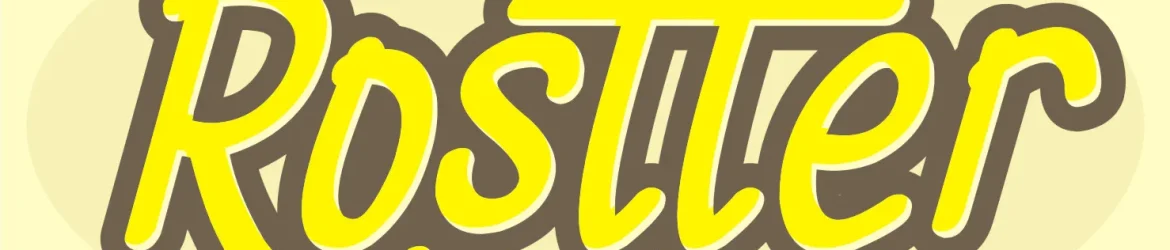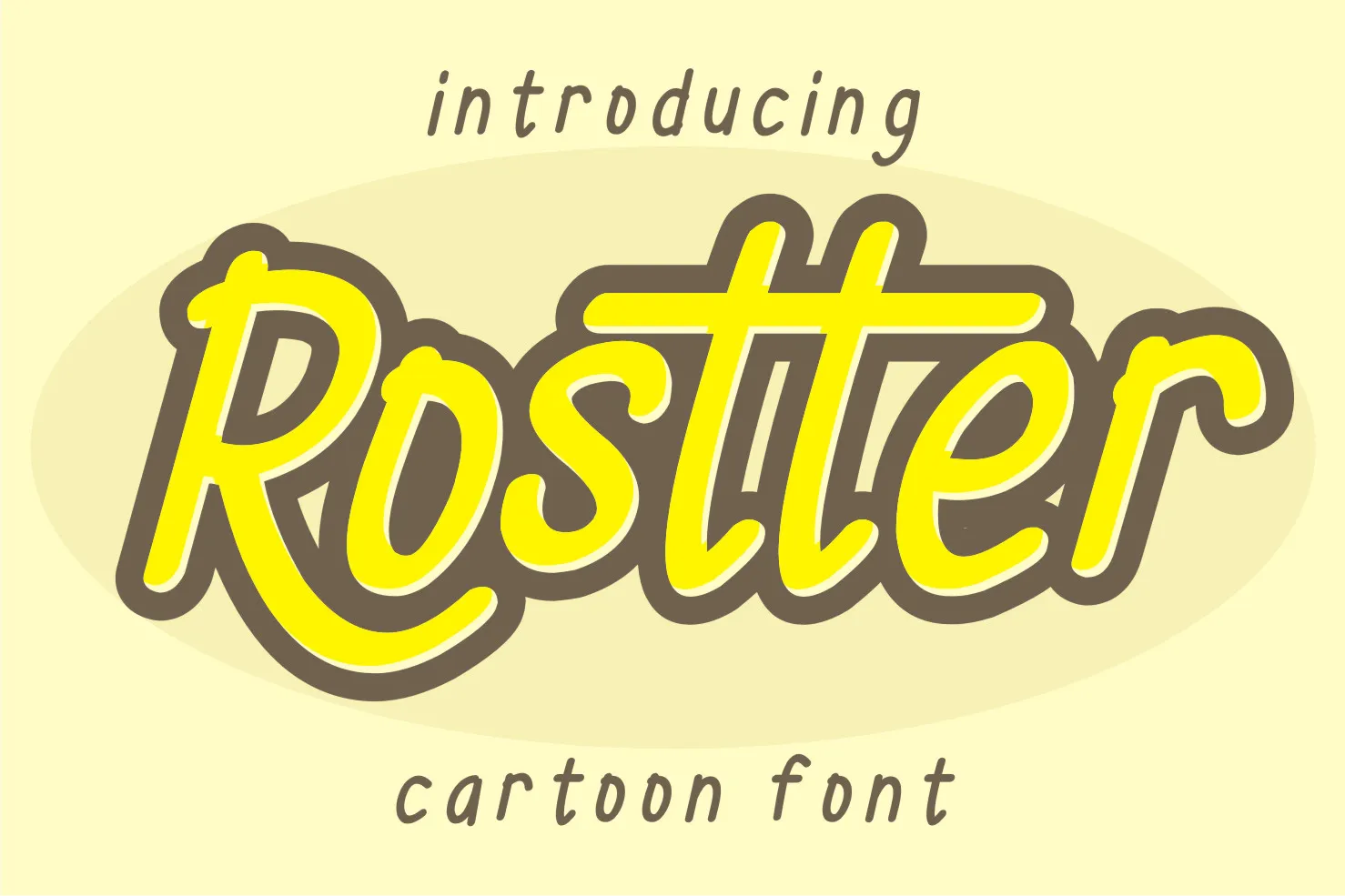
Rostter Display Font – Fonte Grátis
Rostter Display Font
Esta é uma fonte tipo ‘Rostter Display Font’ que oferece um aspecto divertido e atual. Independente do assunto ou tema da sua criação, esta fonte pode transformar qualquer design em algo único e incrivelmente interessante para adicionar ao seu catálogo de fontes. A letra vibrante desta fonte irá tornar suas ideias mais vivas e atrativas. Para quem está procurando uma fonte que dê um toque divertido e inovador a seus projetos, ‘Rostter Display Font’ da designer letterfiastudio é uma ótima escolha. Com sua aparência descontraída e atual, esta fonte vai se tornar um tesouro valioso na sua biblioteca de fontes. Se você está buscando adicionar personalidade a seus designs em vez de usar apenas o básico padrão, ‘Rostter Display Font’ é uma opção perfeita. Suas linhas curvas e traços diferentes adicionam vida ao texto, tornando seu design mais atraente para leitores. Com ‘Rostter Display Font’, você pode realmente fazer o seu design soar único.